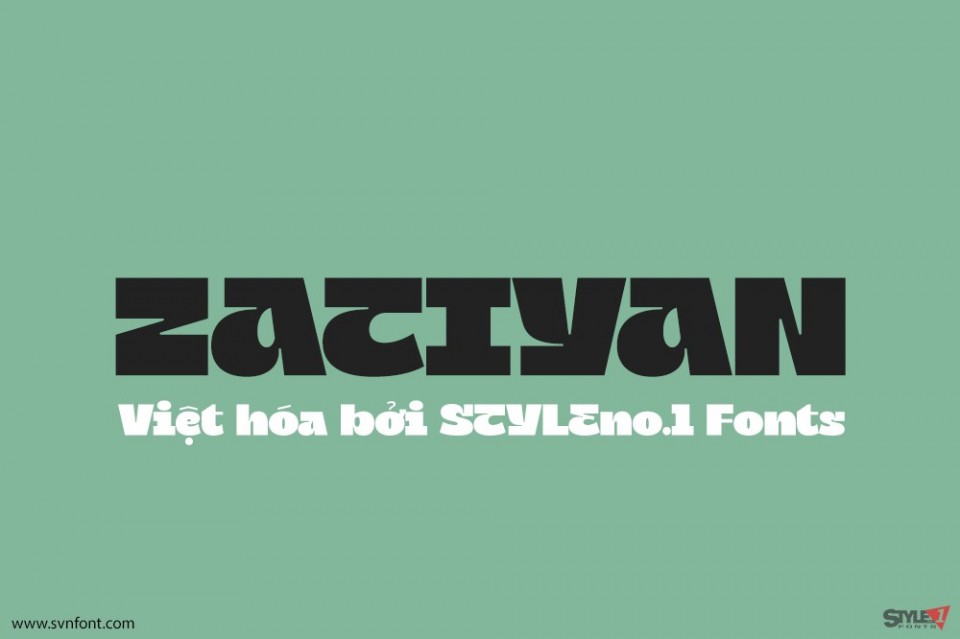
Font việt hóa SVN Zatiyan
Font việt hóa SVN Zatiyan – Nghệ thuật Typography hiện đại cho thiết kế
Trong thế giới đồ họa hiện nay, việc lựa chọn một Font Miễn Phí chất lượng đóng vai trò quan trọng trong việc tạo nên dấu ấn riêng cho tác phẩm. Font việt hóa SVN Zatiyan nổi lên như một giải pháp hoàn hảo cho những ai đang tìm kiếm sự kết hợp giữa nét thanh lịch cổ điển và sự tinh tế hiện đại. Bộ font này không chỉ giúp bài thiết kế trở nên nổi bật mà còn đảm bảo tính chuyên nghiệp, đáp ứng tốt các tiêu chuẩn thẩm mỹ khắt khe nhất của cộng đồng designer Việt Nam hiện nay.
Khám phá đặc điểm nổi bật của Font việt hóa SVN Zatiyan
Phong cách thiết kế độc đáo và linh hoạt
Font việt hóa SVN Zatiyan sở hữu những đường nét uốn lượn mềm mại nhưng vẫn giữ được cấu trúc chắc chắn. Đây là loại font chữ cực kỳ phù hợp cho các tiêu đề lớn, bìa sách hoặc các tấm thiệp mời trang trọng. Nhờ sự cân bằng trong tỷ lệ các ký tự, SVN Zatiyan giúp người xem dễ dàng tiếp nhận thông tin mà không gây cảm giác mỏi mắt hay rối rắm khi đọc các đoạn văn bản dài.
Tối ưu hóa tiếng Việt và tính ứng dụng cao
Điểm mạnh lớn nhất của Font việt hóa SVN Zatiyan chính là việc các dấu tiếng Việt được tinh chỉnh tỉ mỉ, không bị lỗi hiển thị khi gõ văn bản phức tạp. SVN Zatiyan thường được các giáo viên và học sinh ưu tiên sử dụng trong các bài thuyết trình hay thiết kế báo tường nhờ vẻ ngoài chỉn chu. Bạn có thể dễ dàng sử dụng bộ font này trên các phần mềm phổ biến như Photoshop, Illustrator hay cả Microsoft Office.